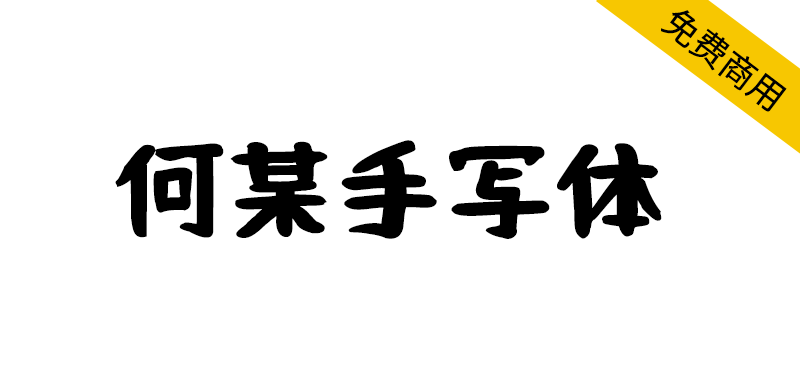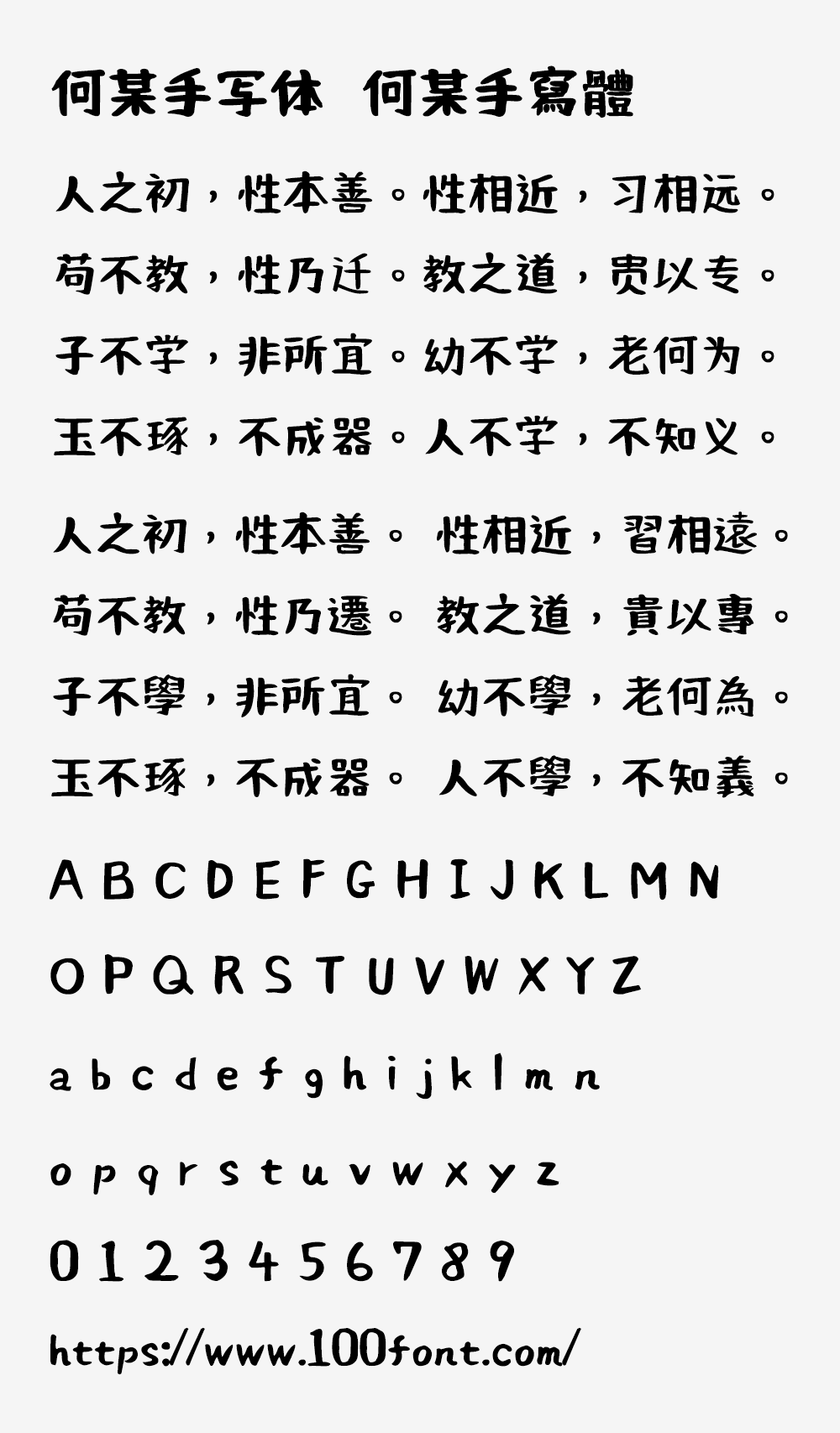
何某手写体是基于おつとめフォント的开放原始码中文字型,与原作者的主要差异是调整部件写法、新增中文字、增加为5个字重、增加一些符号。可以免费商用,欢迎大家自由应用、自由优化、自由改作!
何某手写体与原作者的差异:从原作者的2020-11-21 Ver3.10 (RC) 复制出来修改,修改前,符号+文字数:8784个,修改后,符号+文字数:23739个,中文补字10676个,与原作者重覆造字,考虑文字部件在地区用法不同,所以没有使用原作者字有:凊婧楂癤祅祜祹稹腧薌迁迨迮逈逭靚饘鱁。
字体特色:弥补繁体中文常用字缺字缺憾,调整为5种字重,标点符号位置调整为台湾常见的置中用法,一些部件的写法修改为台湾常见写法。